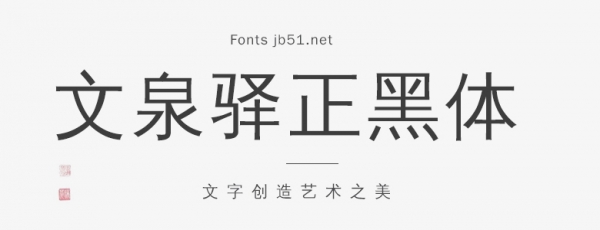
文泉驛正黑體是一個”自由字體“。該字體包含了所有常用簡體中文、繁體中文所需要的漢字(最新版本包含超過27842個漢字,完整覆蓋GB2312/Big5/GBK以及GB18030標準字符集)。該字體同時還包含了日文、韓文和其他幾十種語言符號。除此以外,該字體還嵌入了最新版本的文泉驛點陣宋體的中英文點陣,使得屏幕漢字顯示清晰銳利,易于閱讀。
作為黑體中文字體,文泉驛正黑為非襯線字體,筆畫對比度明顯,特別適合屏幕漢字顯示以及文檔標題字體。